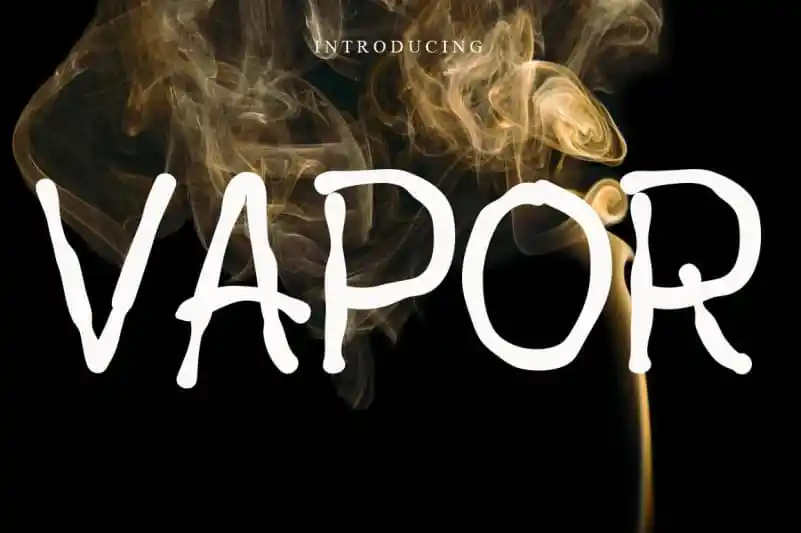
Vapor Display Font – Download Grátis
A fonte Vapor Display Font é uma escolha perfeita para quem busca algo que seja ao mesmo tempo cool e infantil. Seja você designer gráfico, criando arte digital ou fazendo apresentações, ou até mesmo quando você está trabalhando na produção de cartões de agradecimento, essa fonte combina o bom gosto com um toque irreverente. A vapor Display Font não é apenas uma escolha para seus projetos digitais; ela também pode agregar uma nota única e divertida à sua identidade visual. Seja você criando arte digital, produzindo cartões de agradecimento ou dando uma dinâmica inovadora às suas apresentações, Vapor Display Font está sempre pronto para dar um toque especial em seus trabalhos. Ideal tanto para as aplicações mais formais quanto para aquelas que exigem um pouco mais de personalidade, a vapor Display Font é certamente o companheiro perfeito do seu trabalho.